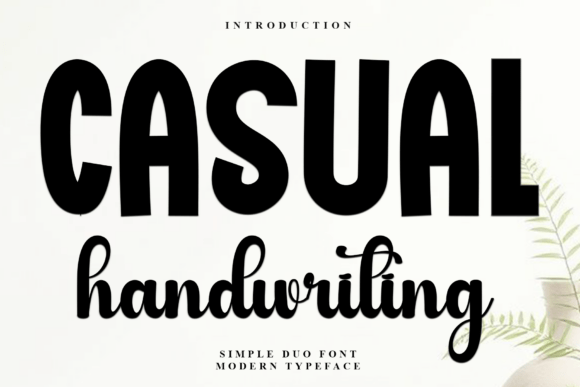
Casual Handwriting
Casual Handwriting์™€ ๊ฐ™์€ ๊ณ ํ’ˆ์งˆ ์ž์‚ฐ์„ ์ฐพ๊ณ  ์žˆ๋‹ค๋ฉด ์ด ํ”„๋ฆฌ๋ฏธ์—„ ํŒจํ‚ค์ง€๋Š” ์ฐฝ์˜์ ์ธ ํ”„๋กœ์ ํŠธ๋ฅผ ์œ„ํ•œ ํ™˜์ƒ์ ์ธ ์„ ํƒ์ž…๋‹ˆ๋‹ค.
POD(์ฃผ๋ฌธํ˜• ์ธ์‡„) ์ œํ’ˆ, ๊ฒฐํ˜ผ์‹ ์ดˆ๋Œ€์žฅ ๋˜๋Š” ์†Œ์…œ ๋ฏธ๋””์–ด ๊ทธ๋ž˜ํ”ฝ์„ ๋งŒ๋“ค ๋•Œ Casual Handwriting๋Š” ์ด์ƒ์ ์ธ ์„ ํƒ์ž…๋‹ˆ๋‹ค.